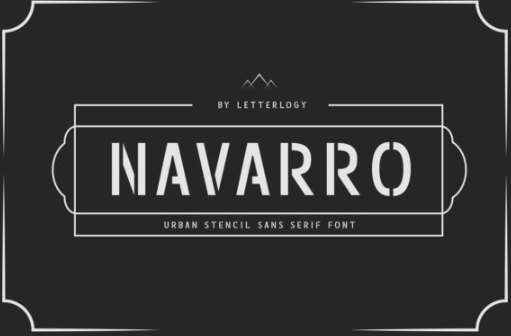
[Creativefabrica] Navarro Font (2022)
ΠŸΡ€Π΅Π΄ΡΡ‚Π°Π²Π»ΡΠ΅ΠΌ Navarro!
Π Π΅Ρ‚Ρ€ΠΎ- ΠΈ Π²ΠΈΠ½Ρ‚Π°ΠΆΠ½Ρ‹ΠΉ городской ΡˆΡ€ΠΈΡ„Ρ‚ с засСчками ΠΈ Ρ‚Ρ€Π°Ρ„Π°Ρ€Π΅Ρ‚Π°ΠΌΠΈ ΠΏΡ€ΠΈΠ·Π²Π°Π½ привнСсти Π³Ρ€Π°Π½ΠΆ ΠΈ Π·Π΅Ρ€Π½ΠΈΡΡ‚ΠΎΡΡ‚ΡŒ городских ΠΏΠ΅ΠΉΠ·Π°ΠΆΠ΅ΠΉ ΠΏΡ€ΠΎΡˆΠ»ΠΎΠ³ΠΎ Π² ваши ΠΏΡ€ΠΎΠ΅ΠΊΡ‚Ρ‹ благодаря своСй простой гСомСтричСской Ρ„ΠΎΡ€ΠΌΠ΅ ΠΈ властному Π²ΠΈΠ΄Ρƒ.
Π˜Π΄Π΅Π°Π»ΡŒΠ½Ρ‹ΠΉ компаньон для Π²Π°ΡˆΠΈΡ… Π²ΠΈΠ½Ρ‚Π°ΠΆΠ½Ρ‹Ρ… ΠΈ Ρ€Π΅Ρ‚Ρ€ΠΎ городских ΠΏΡ€ΠΎΠ΅ΠΊΡ‚ΠΎΠ² ΠΈ дисплССв.